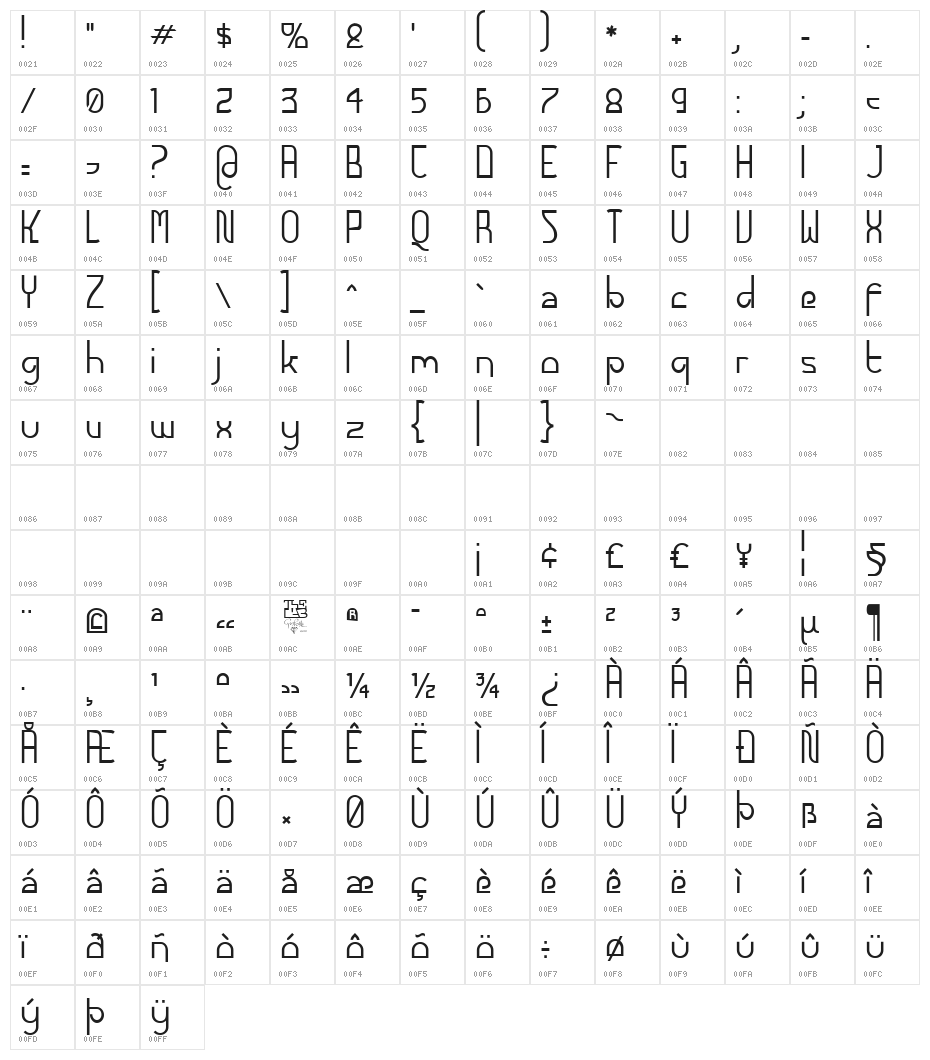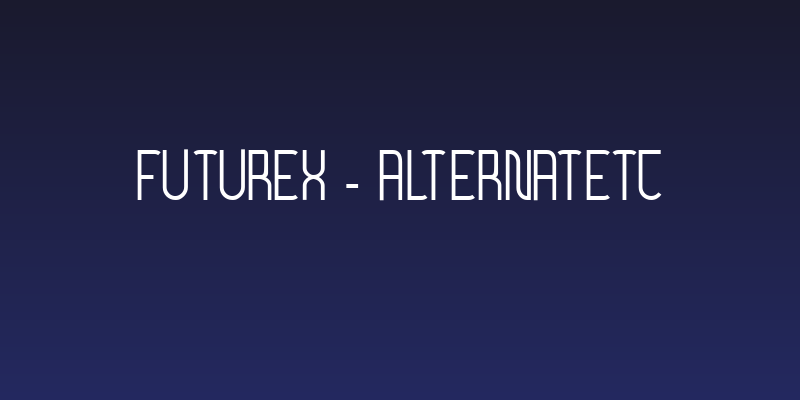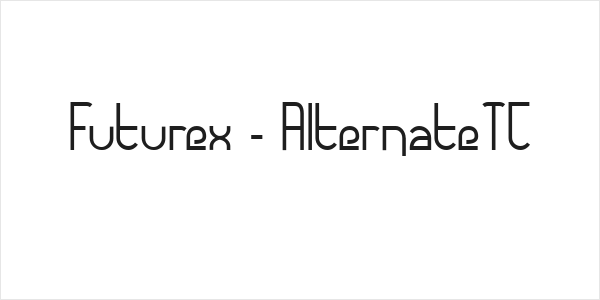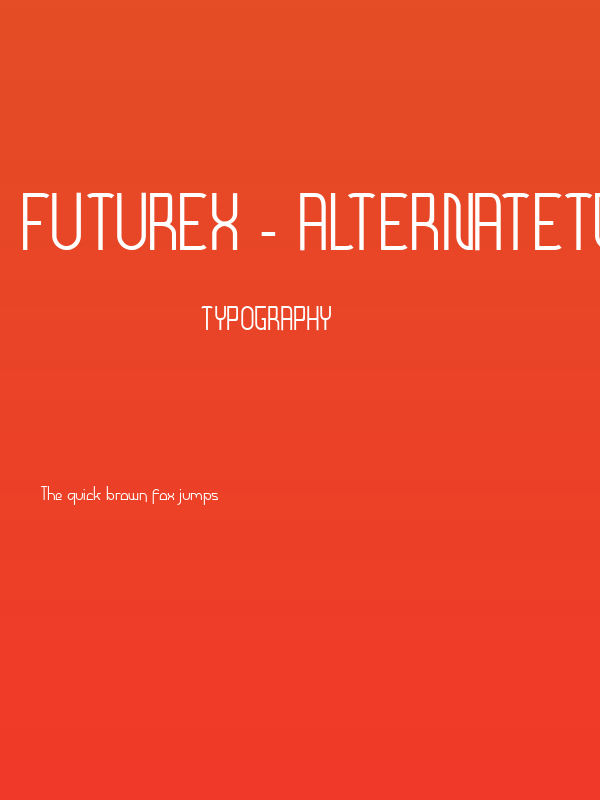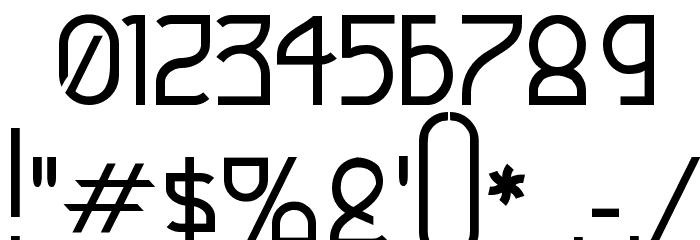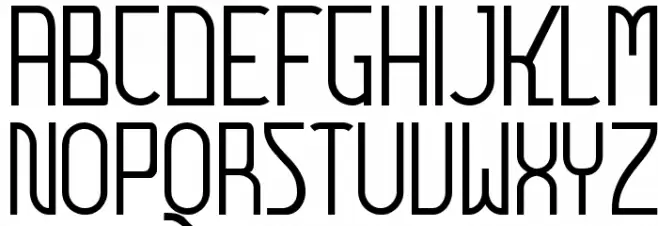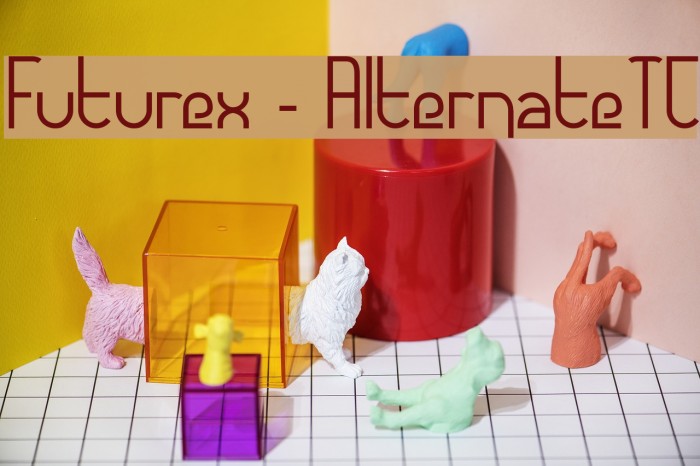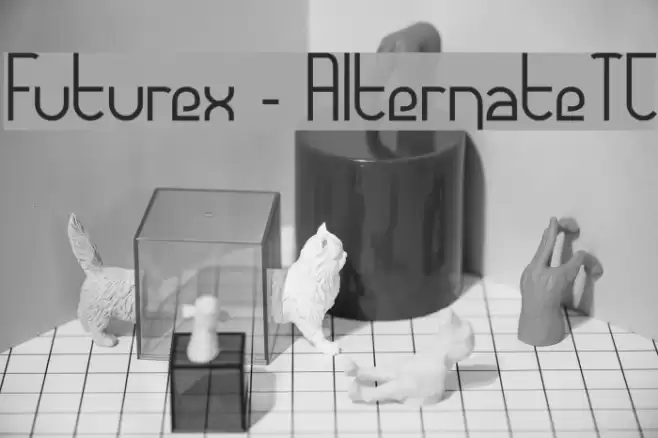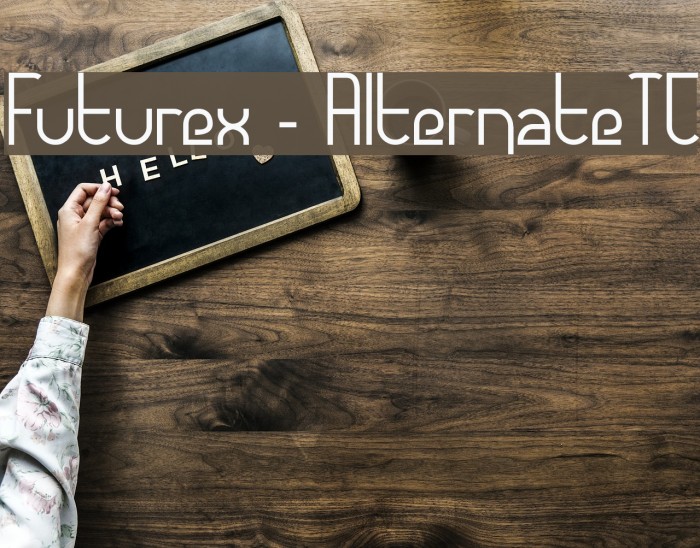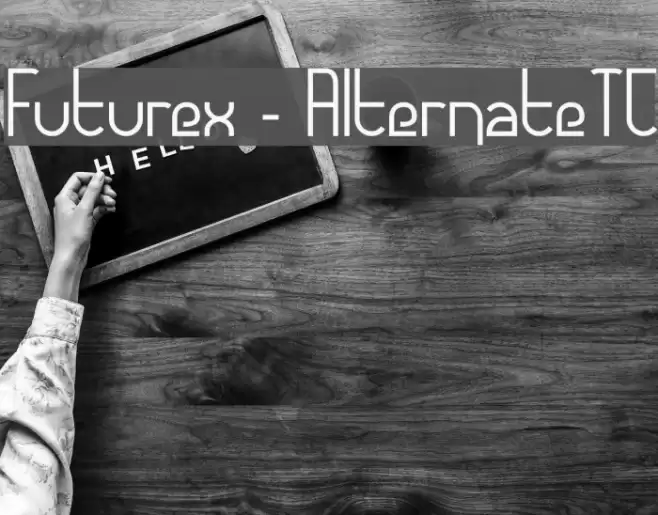
Futurex - AlternateTC Font
| Gesamtstil | Modern, Geometric |
| Anwendungsfall | Headlines, Logos, Digital Interfaces |
| Vorgeschlagene Projekte | Ideal for technology branding, digital interfaces, and innovative product designs. |